漢字の異体字をIVS(異体字シーケンス)で呼び出せるように「基底文字のUnicode」、「VS(異体字セレクタ)」、「字形イメージ」が登録されているデータベースのことです。
基本となるUnicode(基底文字)の後ろに、「VS(異体字セレクタ)」という名の枝番号を付加することで、特定の異体字をピンポイントで指定して呼び出す仕組みのことです。VS自体も基本多言語面(U+FE00〜)や第14面(U+E0100〜)に配置されているUnicodeです。「どの文字にどの枝番号を割り当てるか」というルールは、国際的な「IVD(漢字異体字データベース)」に登録され共有されています。
米国Adobe社によって制定されたグリフセットでUnicodeやJISに依存しない独自の文字集合となっています。Adobe-Japan1-3は9,354字、Adobe-Japan1-4は15,444字のグリフセットです。親字+異体字の考え方を取り入れ、非漢字の拡張や英数字の完備など、充実した文字集合となっています。イワタのオープンタイプフォントはこの文字セットに準拠しています。一般的にAdobe-Japan1-3のセットをStd(スタンダード)版、Adobe-Japan1-4のセットをPro(プロ)版と呼んでいます。
主にUNIX系OSやWebサーバー環境で広く使われてきた日本語の符号化方式です。
同じ意味・読みを持ちながら形が異なる文字のことです。人名に多く、例えば「高」と「髙」、「峰」と「峯」、「辺・邉・邊」などがあります。
共同通信社が定めたK-JIS文字セットの外字の他、ラジオ・テレビ欄用文字、地名・人名に使用される特殊な漢字、新聞組版に必要な記号類、拡張漢字、異体字を追加したシフトJISベースの文字セットです。イワタ新聞書体Ver.4のKJIS版(TrueType/CIDとも)に標準装備しています。尚、OpenTypeにはKJIS外字を含んでいません。
DTPセンタービブロスのBiblos外字の文字種とコードに準拠したシフトJISベースの文字セットです。ポップ4書体(丸ポップ体B/角ポップ体B/角ポップ体E/勘亭流)を除くイワタ一般書体Ver.4(TrueType/CID)に標準装備しています。尚、OpenTypeにはPlus外字を含んでいません。
新聞見出しに特化したイワタU-PRESSです。英数字の高さを漢字の高さに合わせている他、英数字,句読点,約物などを新聞組版に適したデザインにしています。
共同通信社が定めたU-PRESSにイワタ独自の外字を追加した文字セットです。U-PRESSに含まれていないK-JIS文字の他、BSデジタル文字、IBM・NEC外字などを含んでおり、90年版JISやK-JISの完全上位互換になるのはもちろん、プロフェッショナルな新聞制作に必要な文字を網羅しています。
仮名漢字変換ソフトウェアのことを言います。キーボードから仮名文字や(相当する)英字を入力して、それを漢字や平かなに変換します。漢字変換には「かな・漢字辞書」が必要で、各FEPは独自の辞書を持つことが必要です。このため各FEP間での互換性はありません。メジャーなFEPとして、ATOK・EGBRIDGE・IME・ことえりなどがあります。
Unicodeという広大な器を使って、コンピュータが実際に効率よく通信・保存できるようにデータの並び(バイト列)を変換する処理またはその変換ルールのことをいいます。
文字を画面・紙面に埋め込んで例えば、情報の受け手側に送り手側と同じフォントが無くてもその文書が読めるようする技術です。PDFファイルを作成するアプリケーションソフト(Adobe社のAcrobatなど)と埋め込み可能なフォント(エンベッド可のフォント。イワタ書体は全てエンベッド可です。)が必要です。Illustratorなどでフォントをアウトライン化するのとは違う仕組みです。
Original Equipment Manufacturing. 自社ブランドの商品を市場に売り出すに当たって、その部品(フォント)を外部のメーカーに供給させることを言います。この場合、依頼元のブランドイメージを損なうことの無いように、フォントの供給先の品質が極めて重視されます。弊社では大手新聞社、印刷会社、電子機器メーカーに多くのフォントをOEM提供しています。
より適切な字形への置き換えや文字詰めなど、美しく高度な組版に対応するためのOpenTypeフォント(OpenTypeテーブルを実装したTrueTypeを含む)特有の機能を指し、Adobe社製のアプリケーションやOfficeの一部で使用することができます。フォントごとに搭載機能には違いがありビルドの際に設定します。
使用頻度が高い例としては欧文合字があります。例えば「ff」や「fi」と入力すると文字同士がくっついた「合字」に変換されるのはこの機能のはたらきです。
Adobe社とMicrosoftが共同で開発したフォントフォーマット。拡張子は.otfです。WindowsとMacintosh両方のプラットフォームで使用できます。異体字切り替え機能、字詰め(プロポーショナルメトリクス)などの情報が搭載されており、きれいな組版ができる高機能なフォントです。
搭載されている文字数は日本語フォントではAdobeが制定している文字セットに準拠することが多く、Adobe-Japan1-6で23058文字、Adobe-Japan1-7 ではAdobe-Japan1-6に令和合字が追加され23060グリフ収録されています。2025年現在、Adobe-Japan1-7が一番文字数が多いセットです。
フォントテーブルの1つ。ウェイト情報や、サポートする言語のUnicodeの範囲、収容されている全グリフの縦方向の最大・最小値を載せます。OSにフォントをインストールし、アプリでフォントを表示させる上で重要な情報を書き込むテーブルです。
教育に関連する書物や教育現場にて制作される問題集や副読本に使用することを目的として開発されたフォントです。字形は当時の文部省が定めた学習指導要領に準拠しています。
現在イワタでは学参組版に必要な1,062字の外字を含めた12書体の学参フォントと筆順を表現することができる筆順フォントを販売しております。
全国の戸籍文字などをデジタル化するために整備された文字情報基盤をもとにさらに拡張した約7万文字の文字セットでありデータベースです。
文字そのものの「形」のことです。コードが割り当てられているかどうかに関わらず、フォント内に収録されている個々の字形のことをグリフと呼びます。
UTF-16において、2バイト(16ビット)に収まらない文字(Unicodeの第1面以降に配置された文字など)を表現するために、2つの16ビット(計4バイト)をセットにして1つの文字を表す仕組みのことです。
上位サロゲート(D800~DBFFの1024通り)と下位サロゲート(DC00~DFFFの1024通り)の組み合わせによって、約100万文字分の新しい文字を表現できます。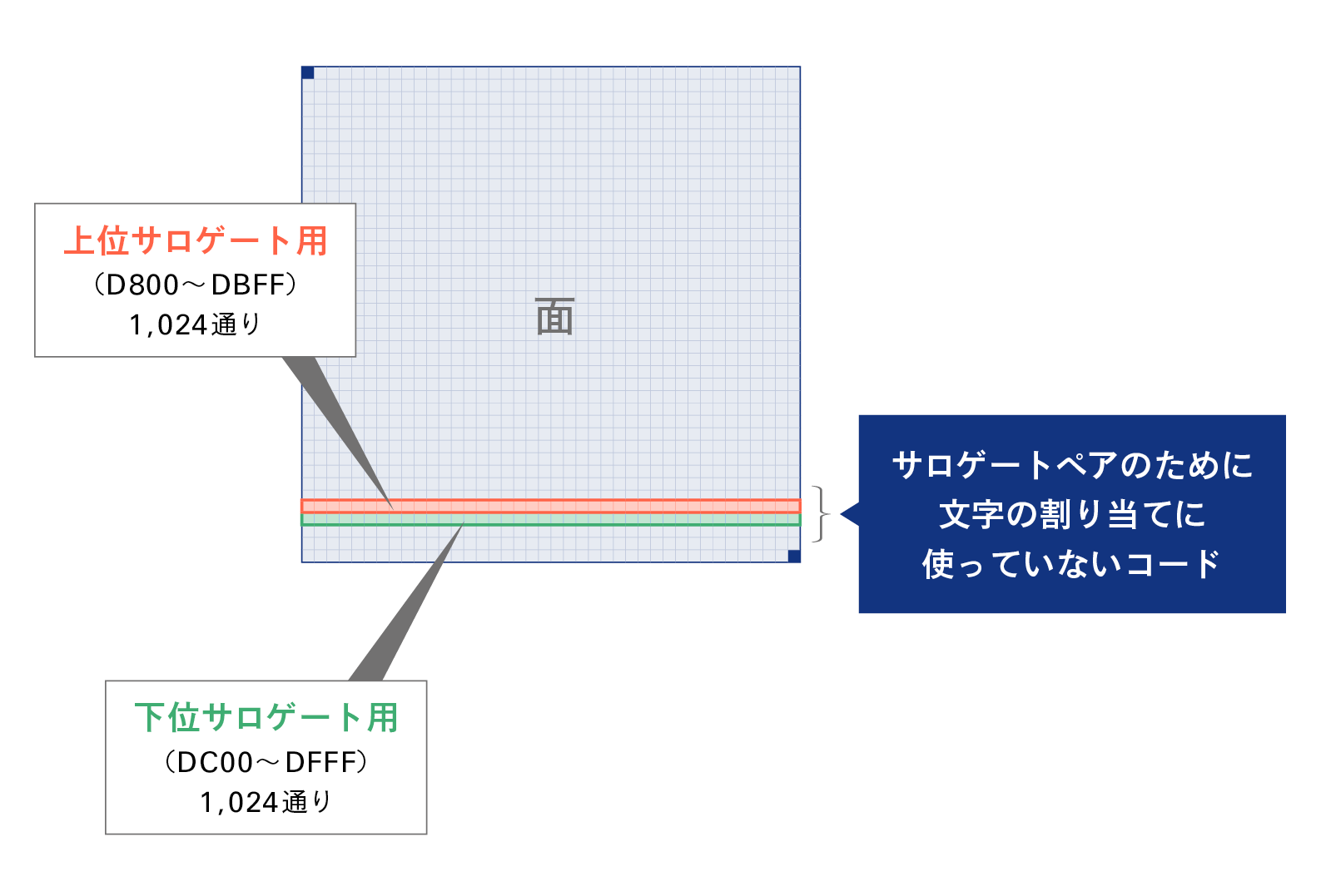
Adobe社が文字の字形それぞれに割り当てた固有の識別番号。CID8267は「2点しんにょうの辻」のように、番号が決まれば一意的に字形が決まります。
フォントテーブルの1つで、OpenTypeフォントのグリフデータです。グリフのデータは、PostScript形式で3次ベジェ曲線で描きます。
OpenTypeフォントやTrueTypeフォントの個々のグリフに付けられている通し番号です。フォント内部で機械的に割り振られるためCIDのように字形と紐付けられることはありません。
フォントのテーブルの1つで、縦書き文字、異体字切り替え、合字などの文字の置き換え機能が搭載されている箇所です。
小さい「ゃ」「ゅ」「ょ」を縦書きにすると他の文字と右のラインが揃ったグリフになったり、「ff」や「fi」を入力すると文字同士がくっついた「合字」に変換されるのはこのGSUB機能のはたらきです。
Unicodeにおいて、中国(C)・日本(J)・韓国(K)で使われている漢字のうち、形が似ていて、由来が同じ漢字をまとめ(統合し)、共通のコードポイントを割り当てた漢字群のことです。
フォントテーブルの1つ。POS(ポス)はポジショニング=位置を決めるという意味で、主にグリフをどれぐらいツメるかの情報が載っています。
「VA」や「Ta」など隙間が目立つグリフの組み合わせには個別にペアカーニングという設定を行います。
フォントテーブルの1つで、Unicode番号とグリフの対応づけをします。例えば「A」にはU+0041というUnicodeが割り当てられています。
1969年に制定された日本初の文字コード規格(旧称:JIS C 6220)です。いわゆる半角英数字と半角カタカナなどが規定されています。また、CR・LFやDEL(0x7F)など、機器の動作を制御するためのコード(制御文字)も定義されています。
1978年に制定された日本の全角文字の標準的な文字コード規格です。16ビット(2バイト)体系を採用し、ひらがな、カタカナ、記号、および第1水準・第2水準の漢字(6,355字)などを規定しています。日本語フォントのベースとして、あらゆる日本語フォントに収容されています。
JIS X 0208:1983に入りきらなかった人名・地名などの漢字を追加するために1990年に制定されました。正式名称は「情報交換用漢字符号―補助漢字」のため、通称「補助漢字」と言われていますが、アクセント記号付きのラテン文字、ギリシア文字・キリル文字など非漢字も収録されています。
JIS X 0208を拡張するために2000年に制定されました。JIS X 0208に含まれない地名・人名用漢字、記号などが第3水準・第4水準として追加されました。2004年に10文字の追加と168字の例示字形の変更が行われました。JIS X 0213はJIS X 0208とセットで使用するものです。
コンピュータがJIS X 0201(半角文字)とJIS X 0208(全角文字)を識別できるように、1980年代に考案された符号化方式です。パソコン黎明期からMS-DOSやWindows、Classic Mac OSなどで標準的に使われてきました。今でも日本語OpenTypeフォントにはShift_JIS用のcmapを実装しているものがあります。
Adobe社のInDesignにて外字を使用するためのプラグインテクノロジーです。形状と付属情報等からなる文字データを文書内に埋め込むことを基本概念としています。イワタはこのSINGに対応した外字セット、外字作成ツール等の製品を順次開発、販売していきます。
た行
フォントファイルの内部で使用している構造のことです。目的別に、字形を入れておく所、文字コードを入れておく所など、管理しやすいように仕切られています。
デジタルコンテンツををスマホ、PCや専用のデバイスなどで読む形式の「書籍」です。
二者の漢字が同じ文字であると断定すること。
フォントフォーマットの1つで、拡張子は.ttfと.ttcです。 TTFはTrueType Font、TTCはTrueType Collection(複数のTTFを1ファイルにまとめたもの)になります。WindowsPCにデフォルトでインストールされているMSゴシックや游明朝はTureTypeフォントです。イワタの日本語TrueTypeフォントはJIS X 0208とJIS X 0213に準拠して開発しています。
な行
フォントテーブルの1つで、名前関連の情報が載っています。デバイス画面に表示されるフォントの名前(例:イワタ福まるごStdN L)はこのテーブルの情報です。ちなみにイワタフォントのOpenTypeのフォントメニュー名はI-OTF***かイワタ***ですので、フォントを探す際は目印にしてください。
は行
8個のビットを1つにまとめた単位で、1バイト=8ビットです。1バイトでは 2の8乗=256通りの情報を表現できます。英数字は通常1バイト、日本語などの多言語は複数バイト(2〜4バイト)を使って表されます。
コンピュータが扱う情報の最小単位で、「0」または「1」の2つの状態を表します。データの処理や伝送、文字コードのデータ構造における最も基本的な要素です。
フォントメーカーのビルドとは、作成した文字のデータをデバイスでフォントとして使えるように、プログラムを書いてツールで変換すること。変換するツールは、IKARUSやAFDKOを使います。
それ自体では機能せず、特定のアプリケーションソフトに機能を組み込む形で動作するプログラムの総称を言います。通常、アプリケーションによって指定されたフォルダに入れておくだけで動作しますが、アプリケーション側で登録のための操作や何等かの設定を行う必要がある場合もあります。弊社ではInDesignのPlugInソフトとして、株式組版用ソフトを開発・販売しております。
社会全体で共有され、多様なサービスの共通基盤となることを目的に政府が指定・整備している基本データを指します。
フォントテーブルの1つ。フォントデータの概要であるヘッダー情報が記載されます。具体的には更新日時やバージョン、入っている字形の縦方向・横方向の最大・最小値などが書いてあります。
1900年(明治33年)の小学校令で、学校で教えるひらがなが「1音につき1字」に絞り込まれましたが、それ以前に日常的に使われていた多様なひらがなの異体字のことです。Unicode 10.0以降で変体仮名の登録が進みました。
細かなデザインの違いを認めつつ同じ文字として扱うこと。
ま行
コンピュータが文字を処理・表示するために、それぞれの文字に割り当てられた固有の番号のことです。UnicodeやJIS X 0208も文字コードの一種です。
日本の戸籍や住民票など、人名に使われる膨大な漢字のバリエーションを整理した約6万文字に及ぶ文字セットであり、漢字情報やUnicode(IVS)との対応関係が記載されたデータベースのことです。2021年(令和3年)に郵便番号などと並び、社会の基盤となる重要データベース「ベースレジストリ」のひとつとして指定されました。
や行
Unicodeで定義された文字を処理するための符号化方式の一つです。1文字は1〜4バイトの可変長(文字によって長さを変える)で表現されます。MacやWebなどで採用されています。
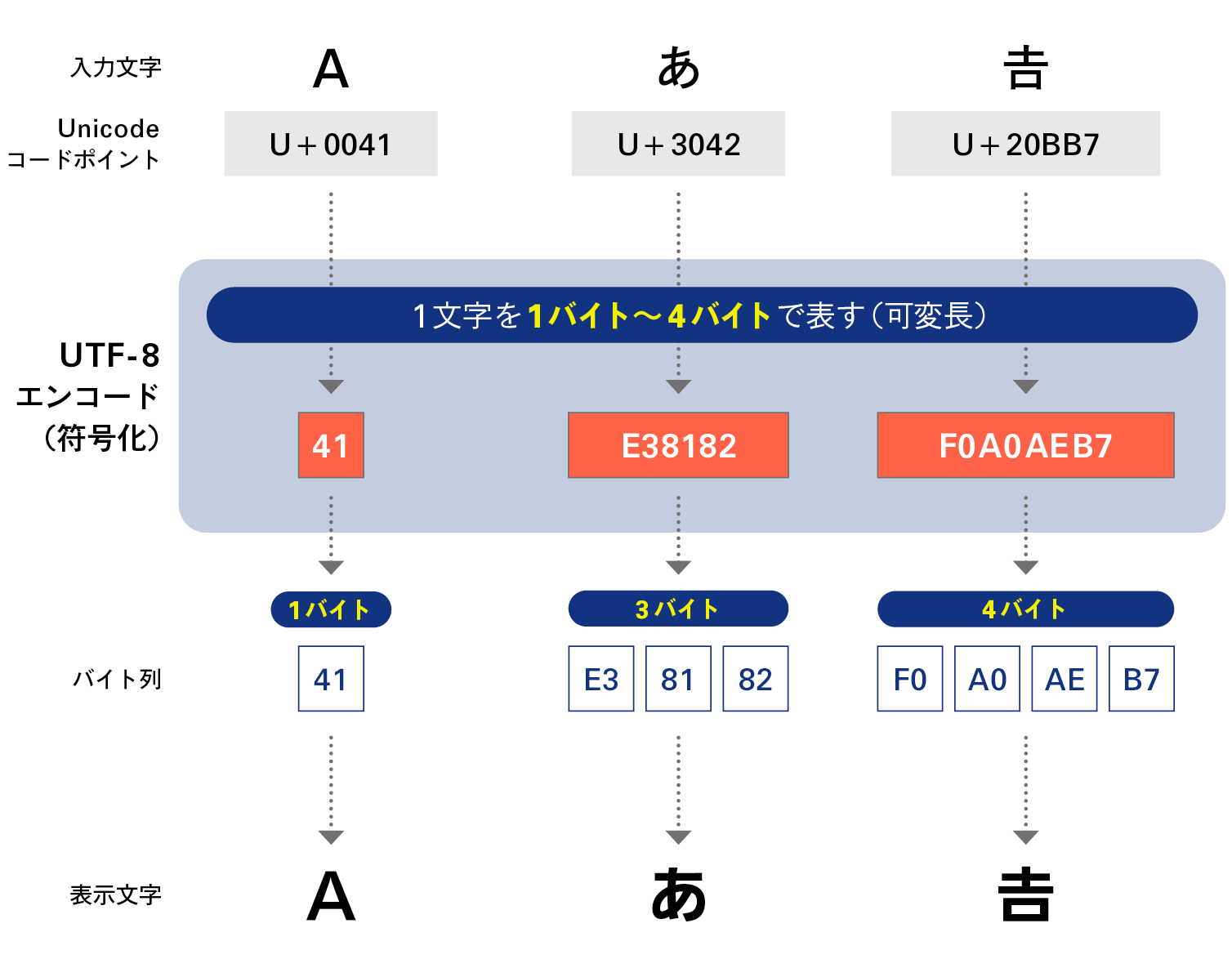
Unicodeで定義された文字を処理するための符号化方式の一つです。1文字は2バイトまたは4バイトで表現されます。Windowsの内部処理などで採用されています。
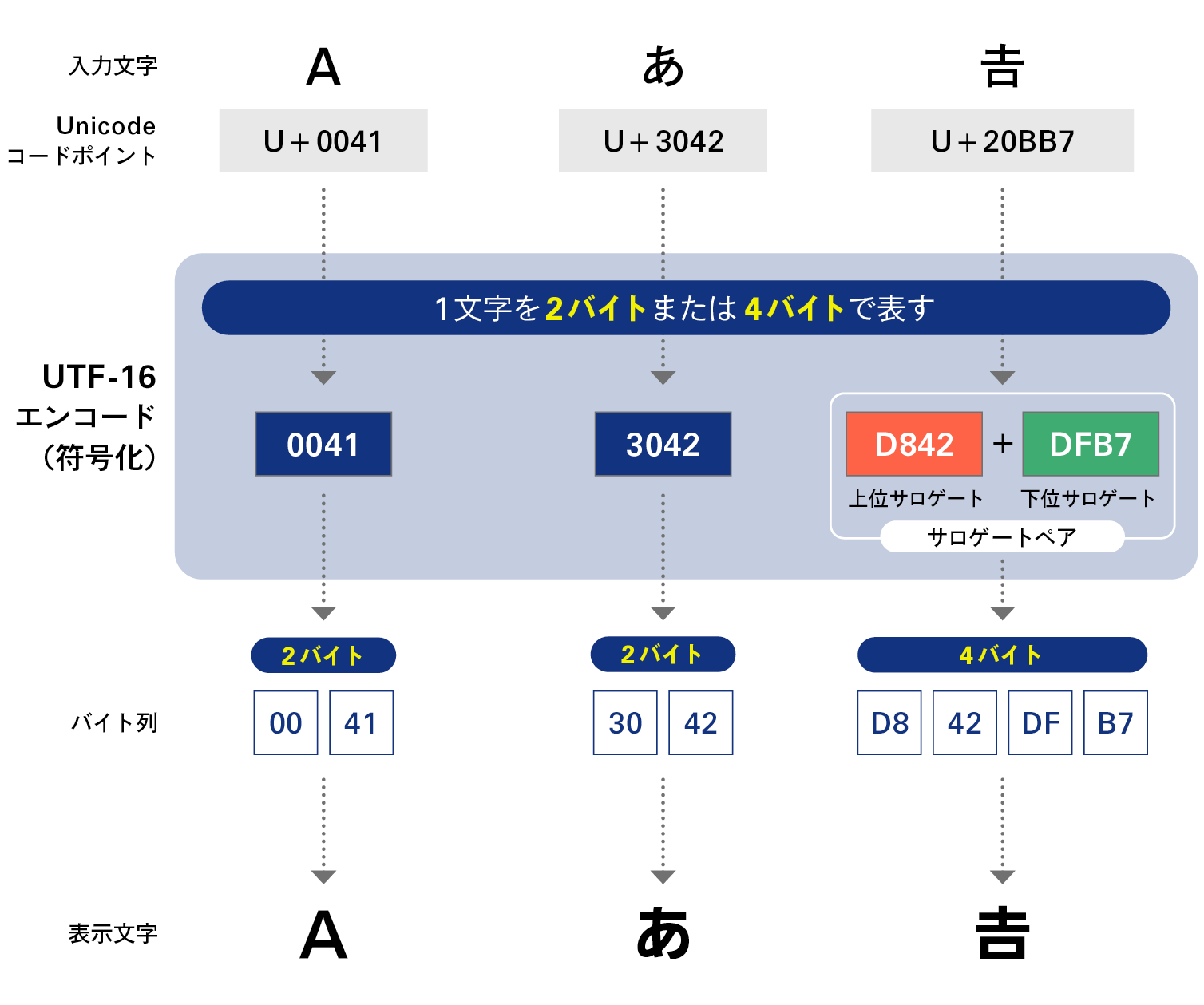
年齢/性別や障害の有無に関係なく、あらゆる人が商品/サービス/住居/施設を快適に利用できるように最初から意図してデザイン・設計をすることを指します。
ユニバーサルデザイン視点に基づき開発したフォントで、弱視、ディスレクシア(読み書き障害)、老眼、白内障等々の視覚障害の人たちにも見やすい文字です。
JISが国内の標準であるのに対して、Unicodeは世界の標準として1文字に固有のコードを付け、世界中の文字を一つの標準で管理しようという発想から制定されたコード体系です。約65,000字のエリアに文字がマッピングされています。また、日本・中国・韓国の文字群は類似文字を集め、包摂基準を設けたCJKというグループに統合されています。
Unicodeの巨大な文字管理スペースを構成する、全17の「面(0~16)」の第0区画です。
U+0000 〜 U+FFFF の範囲(65,536文字分)を指します。日本語のひらがな・カタカナ・常用漢字はもちろん、現代の世界中で使われている主要な言語の文字や基本的な記号の大部分がこの面に収められています。
Unicodeの巨大な文字管理スペースを構成する、全17の「面(0~16)」の第1区画です。
U+10000 〜 U+1FFFF の範囲を指します。歴史的な古代文字や特殊な記号、楽譜、絵文字(Emoji)などがこの面に割り当てられています。
Unicodeの巨大な文字管理スペースを構成する、全17の「面(0~16)」の第2区画です。
U+20000 〜 U+2FFFF の範囲を指します。基本多言語面(BMP)に収まらなかった「JIS第3・第4水準漢字」など、稀少な漢字、人名・地名用の異体字、歴史的典籍に使われる漢字などが割り振られています。
Unicodeの巨大な文字管理スペースを構成する、全17の「面(0~16)」の第3区画です。
U+30000 〜 U+3FFFF の範囲を指します。甲骨文字や金文、篆書体などの古代漢字や近年新しく追加された漢字のためのエリアです。
Unicodeの巨大な文字管理スペースを構成する、全17の「面(0~16)」の第4~13区画です。
U+40000 〜 U+DFFFF の範囲を指します。将来の標準化のために予約されている未定義(未割り当て)の領域です。
Unicodeの巨大な文字管理スペースを構成する、全17の「面(0~16)」の第14区画です。
U+E0000 〜 U+EFFFF の範囲を指します。文字そのものではなく、フォントの異体字をコントロールする「異体字セレクタ(IVS)」などの制御用文字が割り当てられています。
Unicodeの巨大な文字管理スペースを構成する、全17の「面(0~16)」の第15、16区画です。
U+F0000 〜 U+10FFFF の範囲を指します。独自の文字を定義可能な開かれた外字領域(私用領域)です。
A
米国Adobe社によって制定されたグリフセットでUnicodeやJISに依存しない独自の文字集合となっています。Adobe-Japan1-3は9,354字、Adobe-Japan1-4は15,444字のグリフセットです。親字+異体字の考え方を取り入れ、非漢字の拡張や英数字の完備など、充実した文字集合となっています。イワタのオープンタイプフォントはこの文字セットに準拠しています。一般的にAdobe-Japan1-3のセットをStd(スタンダード)版、Adobe-Japan1-4のセットをPro(プロ)版と呼んでいます。
B
コンピュータが扱う情報の最小単位で、「0」または「1」の2つの状態を表します。データの処理や伝送、文字コードのデータ構造における最も基本的な要素です。
フォントメーカーのビルドとは、作成した文字のデータをデバイスでフォントとして使えるように、プログラムを書いてツールで変換すること。変換するツールは、IKARUSやAFDKOを使います。
8個のビットを1つにまとめた単位で、1バイト=8ビットです。1バイトでは 2の8乗=256通りの情報を表現できます。英数字は通常1バイト、日本語などの多言語は複数バイト(2〜4バイト)を使って表されます。
C
フォントテーブルの1つで、OpenTypeフォントのグリフデータです。グリフのデータは、PostScript形式で3次ベジェ曲線で描きます。
Adobe社が文字の字形それぞれに割り当てた固有の識別番号。CID8267は「2点しんにょうの辻」のように、番号が決まれば一意的に字形が決まります。
Unicodeにおいて、中国(C)・日本(J)・韓国(K)で使われている漢字のうち、形が似ていて、由来が同じ漢字をまとめ(統合し)、共通のコードポイントを割り当てた漢字群のことです。
フォントテーブルの1つで、Unicode番号とグリフの対応づけをします。例えば「A」にはU+0041というUnicodeが割り当てられています。
E
文字を画面・紙面に埋め込んで例えば、情報の受け手側に送り手側と同じフォントが無くてもその文書が読めるようする技術です。PDFファイルを作成するアプリケーションソフト(Adobe社のAcrobatなど)と埋め込み可能なフォント(エンベッド可のフォント。イワタ書体は全てエンベッド可です。)が必要です。Illustratorなどでフォントをアウトライン化するのとは違う仕組みです。
主にUNIX系OSやWebサーバー環境で広く使われてきた日本語の符号化方式です。
F
仮名漢字変換ソフトウェアのことを言います。キーボードから仮名文字や(相当する)英字を入力して、それを漢字や平かなに変換します。漢字変換には「かな・漢字辞書」が必要で、各FEPは独自の辞書を持つことが必要です。このため各FEP間での互換性はありません。メジャーなFEPとして、ATOK・EGBRIDGE・IME・ことえりなどがあります。
G
全国の戸籍文字などをデジタル化するために整備された文字情報基盤をもとにさらに拡張した約7万文字の文字セットでありデータベースです。
OpenTypeフォントやTrueTypeフォントの個々のグリフに付けられている通し番号です。フォント内部で機械的に割り振られるためCIDのように字形と紐付けられることはありません。
文字そのものの「形」のことです。コードが割り当てられているかどうかに関わらず、フォント内に収録されている個々の字形のことをグリフと呼びます。
フォントテーブルの1つ。POS(ポス)はポジショニング=位置を決めるという意味で、主にグリフをどれぐらいツメるかの情報が載っています。
「VA」や「Ta」など隙間が目立つグリフの組み合わせには個別にペアカーニングという設定を行います。
フォントのテーブルの1つで、縦書き文字、異体字切り替え、合字などの文字の置き換え機能が搭載されている箇所です。
小さい「ゃ」「ゅ」「ょ」を縦書きにすると他の文字と右のラインが揃ったグリフになったり、「ff」や「fi」を入力すると文字同士がくっついた「合字」に変換されるのはこのGSUB機能のはたらきです。
H
フォントテーブルの1つ。フォントデータの概要であるヘッダー情報が記載されます。具体的には更新日時やバージョン、入っている字形の縦方向・横方向の最大・最小値などが書いてあります。
I
漢字の異体字をIVS(異体字シーケンス)で呼び出せるように「基底文字のUnicode」、「VS(異体字セレクタ)」、「字形イメージ」が登録されているデータベースのことです。
基本となるUnicode(基底文字)の後ろに、「VS(異体字セレクタ)」という名の枝番号を付加することで、特定の異体字をピンポイントで指定して呼び出す仕組みのことです。VS自体も基本多言語面(U+FE00〜)や第14面(U+E0100〜)に配置されているUnicodeです。「どの文字にどの枝番号を割り当てるか」というルールは、国際的な「IVD(漢字異体字データベース)」に登録され共有されています。
J
1969年に制定された日本初の文字コード規格(旧称:JIS C 6220)です。いわゆる半角英数字と半角カタカナなどが規定されています。また、CR・LFやDEL(0x7F)など、機器の動作を制御するためのコード(制御文字)も定義されています。
1978年に制定された日本の全角文字の標準的な文字コード規格です。16ビット(2バイト)体系を採用し、ひらがな、カタカナ、記号、および第1水準・第2水準の漢字(6,355字)などを規定しています。日本語フォントのベースとして、あらゆる日本語フォントに収容されています。
JIS X 0208:1983に入りきらなかった人名・地名などの漢字を追加するために1990年に制定されました。正式名称は「情報交換用漢字符号―補助漢字」のため、通称「補助漢字」と言われていますが、アクセント記号付きのラテン文字、ギリシア文字・キリル文字など非漢字も収録されています。
JIS X 0208を拡張するために2000年に制定されました。JIS X 0208に含まれない地名・人名用漢字、記号などが第3水準・第4水準として追加されました。2004年に10文字の追加と168字の例示字形の変更が行われました。JIS X 0213はJIS X 0208とセットで使用するものです。
M
全国の戸籍文字などをデジタル化するために整備された文字情報基盤をもとにさらに拡張した約7万文字の文字セットでありデータベースです。
N
フォントテーブルの1つで、名前関連の情報が載っています。デバイス画面に表示されるフォントの名前(例:イワタ福まるごStdN L)はこのテーブルの情報です。ちなみにイワタフォントのOpenTypeのフォントメニュー名はI-OTF***かイワタ***ですので、フォントを探す際は目印にしてください。
O
Original Equipment Manufacturing. 自社ブランドの商品を市場に売り出すに当たって、その部品(フォント)を外部のメーカーに供給させることを言います。この場合、依頼元のブランドイメージを損なうことの無いように、フォントの供給先の品質が極めて重視されます。弊社では大手新聞社、印刷会社、電子機器メーカーに多くのフォントをOEM提供しています。
より適切な字形への置き換えや文字詰めなど、美しく高度な組版に対応するためのOpenTypeフォント(OpenTypeテーブルを実装したTrueTypeを含む)特有の機能を指し、Adobe社製のアプリケーションやOfficeの一部で使用することができます。フォントごとに搭載機能には違いがありビルドの際に設定します。
使用頻度が高い例としては欧文合字があります。例えば「ff」や「fi」と入力すると文字同士がくっついた「合字」に変換されるのはこの機能のはたらきです。
Adobe社とMicrosoftが共同で開発したフォントフォーマット。拡張子は.otfです。WindowsとMacintosh両方のプラットフォームで使用できます。異体字切り替え機能、字詰め(プロポーショナルメトリクス)などの情報が搭載されており、きれいな組版ができる高機能なフォントです。
搭載されている文字数は日本語フォントではAdobeが制定している文字セットに準拠することが多く、Adobe-Japan1-6で23058文字、Adobe-Japan1-7 ではAdobe-Japan1-6に令和合字が追加され23060グリフ収録されています。2025年現在、Adobe-Japan1-7が一番文字数が多いセットです。
フォントテーブルの1つ。ウェイト情報や、サポートする言語のUnicodeの範囲、収容されている全グリフの縦方向の最大・最小値を載せます。OSにフォントをインストールし、アプリでフォントを表示させる上で重要な情報を書き込むテーブルです。
P
それ自体では機能せず、特定のアプリケーションソフトに機能を組み込む形で動作するプログラムの総称を言います。通常、アプリケーションによって指定されたフォルダに入れておくだけで動作しますが、アプリケーション側で登録のための操作や何等かの設定を行う必要がある場合もあります。弊社ではInDesignのPlugInソフトとして、株式組版用ソフトを開発・販売しております。
S
コンピュータがJIS X 0201(半角文字)とJIS X 0208(全角文字)を識別できるように、1980年代に考案された符号化方式です。パソコン黎明期からMS-DOSやWindows、Classic Mac OSなどで標準的に使われてきました。今でも日本語OpenTypeフォントにはShift_JIS用のcmapを実装しているものがあります。
Adobe社のInDesignにて外字を使用するためのプラグインテクノロジーです。形状と付属情報等からなる文字データを文書内に埋め込むことを基本概念としています。イワタはこのSINGに対応した外字セット、外字作成ツール等の製品を順次開発、販売していきます。
T
フォントファイルの内部で使用している構造のことです。目的別に、字形を入れておく所、文字コードを入れておく所など、管理しやすいように仕切られています。
U
年齢/性別や障害の有無に関係なく、あらゆる人が商品/サービス/住居/施設を快適に利用できるように最初から意図してデザイン・設計をすることを指します。
ユニバーサルデザイン視点に基づき開発したフォントで、弱視、ディスレクシア(読み書き障害)、老眼、白内障等々の視覚障害の人たちにも見やすい文字です。
JISが国内の標準であるのに対して、Unicodeは世界の標準として1文字に固有のコードを付け、世界中の文字を一つの標準で管理しようという発想から制定されたコード体系です。約65,000字のエリアに文字がマッピングされています。また、日本・中国・韓国の文字群は類似文字を集め、包摂基準を設けたCJKというグループに統合されています。
Unicodeの巨大な文字管理スペースを構成する、全17の「面(0~16)」の第0区画です。
U+0000 〜 U+FFFF の範囲(65,536文字分)を指します。日本語のひらがな・カタカナ・常用漢字はもちろん、現代の世界中で使われている主要な言語の文字や基本的な記号の大部分がこの面に収められています。
Unicodeの巨大な文字管理スペースを構成する、全17の「面(0~16)」の第1区画です。
U+10000 〜 U+1FFFF の範囲を指します。歴史的な古代文字や特殊な記号、楽譜、絵文字(Emoji)などがこの面に割り当てられています。
Unicodeの巨大な文字管理スペースを構成する、全17の「面(0~16)」の第2区画です。
U+20000 〜 U+2FFFF の範囲を指します。基本多言語面(BMP)に収まらなかった「JIS第3・第4水準漢字」など、稀少な漢字、人名・地名用の異体字、歴史的典籍に使われる漢字などが割り振られています。
Unicodeの巨大な文字管理スペースを構成する、全17の「面(0~16)」の第3区画です。
U+30000 〜 U+3FFFF の範囲を指します。甲骨文字や金文、篆書体などの古代漢字や近年新しく追加された漢字のためのエリアです。
Unicodeの巨大な文字管理スペースを構成する、全17の「面(0~16)」の第4~13区画です。
U+40000 〜 U+DFFFF の範囲を指します。将来の標準化のために予約されている未定義(未割り当て)の領域です。
Unicodeの巨大な文字管理スペースを構成する、全17の「面(0~16)」の第14区画です。
U+E0000 〜 U+EFFFF の範囲を指します。文字そのものではなく、フォントの異体字をコントロールする「異体字セレクタ(IVS)」などの制御用文字が割り当てられています。
Unicodeの巨大な文字管理スペースを構成する、全17の「面(0~16)」の第15、16区画です。
U+F0000 〜 U+10FFFF の範囲を指します。独自の文字を定義可能な開かれた外字領域(私用領域)です。
共同通信社がニュースなどの配信を目的に定めたUCS準拠の文字セットです。基本的に表外漢字を採用した改訂版JISの字形に合わせているため、90年版JISとは一部互換性がありません。
Unicodeで定義された文字を処理するための符号化方式の一つです。1文字は1〜4バイトの可変長(文字によって長さを変える)で表現されます。MacやWebなどで採用されています。
Unicodeで定義された文字を処理するための符号化方式の一つです。1文字は2バイトまたは4バイトで表現されます。Windowsの内部処理などで採用されています。